A kézzel készített papírcsodák újabb állomására érkeztünk.
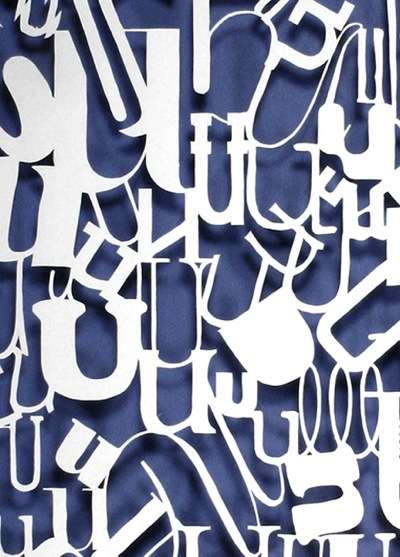
A kézzel készített papírcsodák újabb állomására érkeztünk. Ha már magatokhoz tértetek Peter Callesen műveitől, akkor figyelmetekbe ajánljuk ezeket a posztereket.
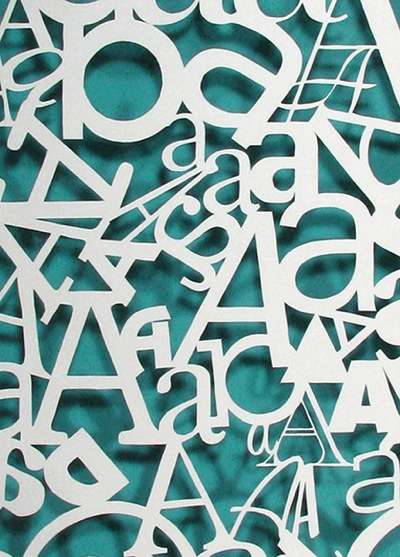
A rendkívűl időigényes elkészítés eredményei ezek a különböző betűstílusokat összesűrítő poszterek.